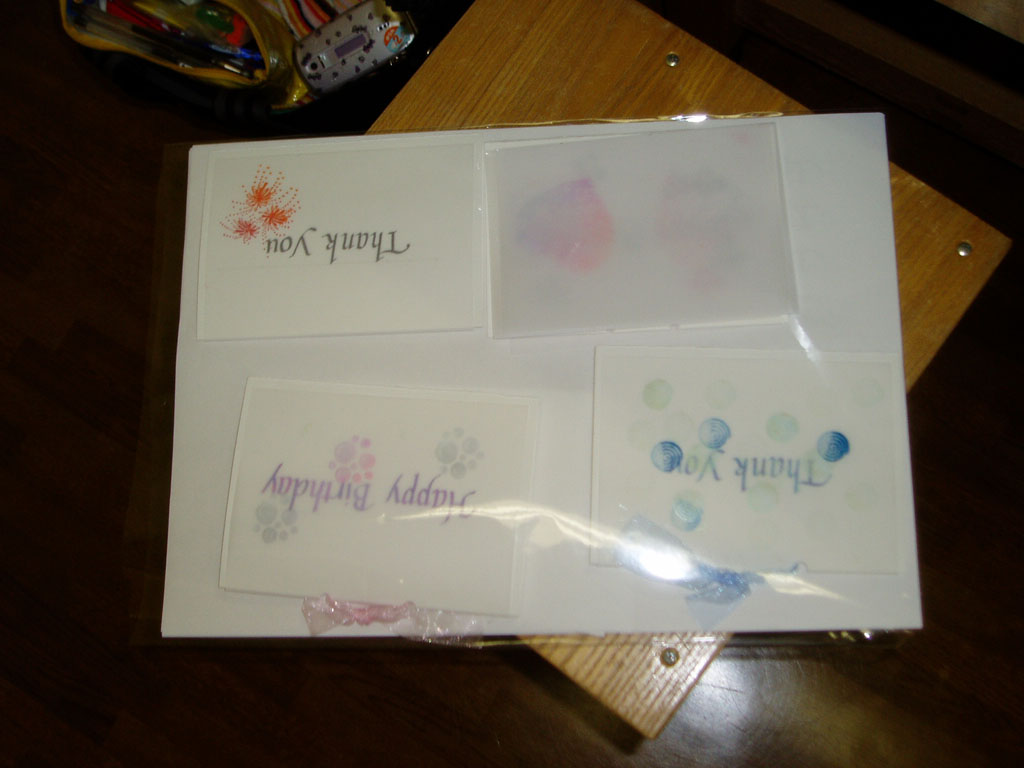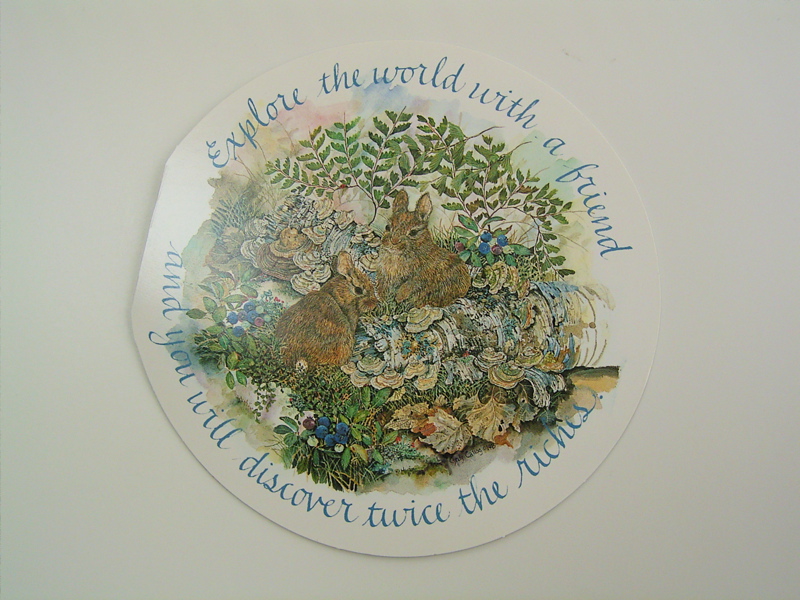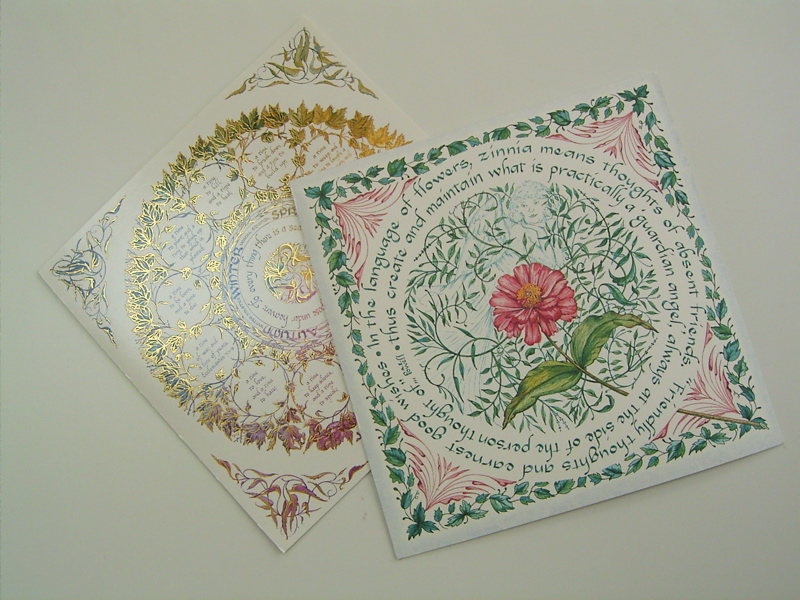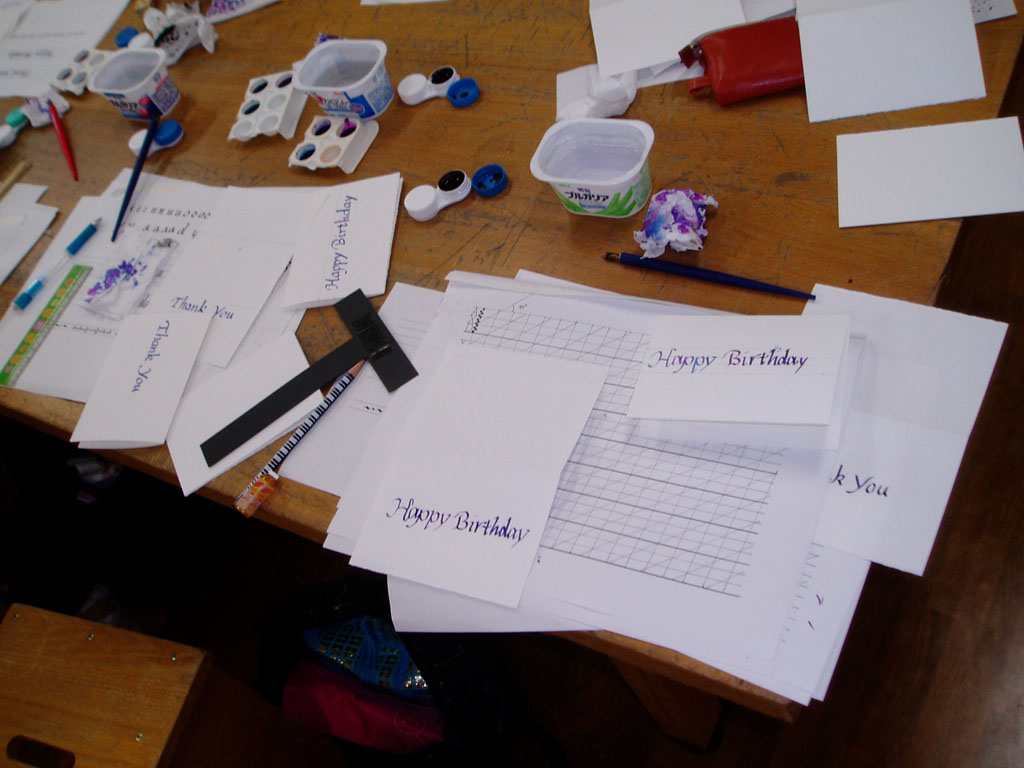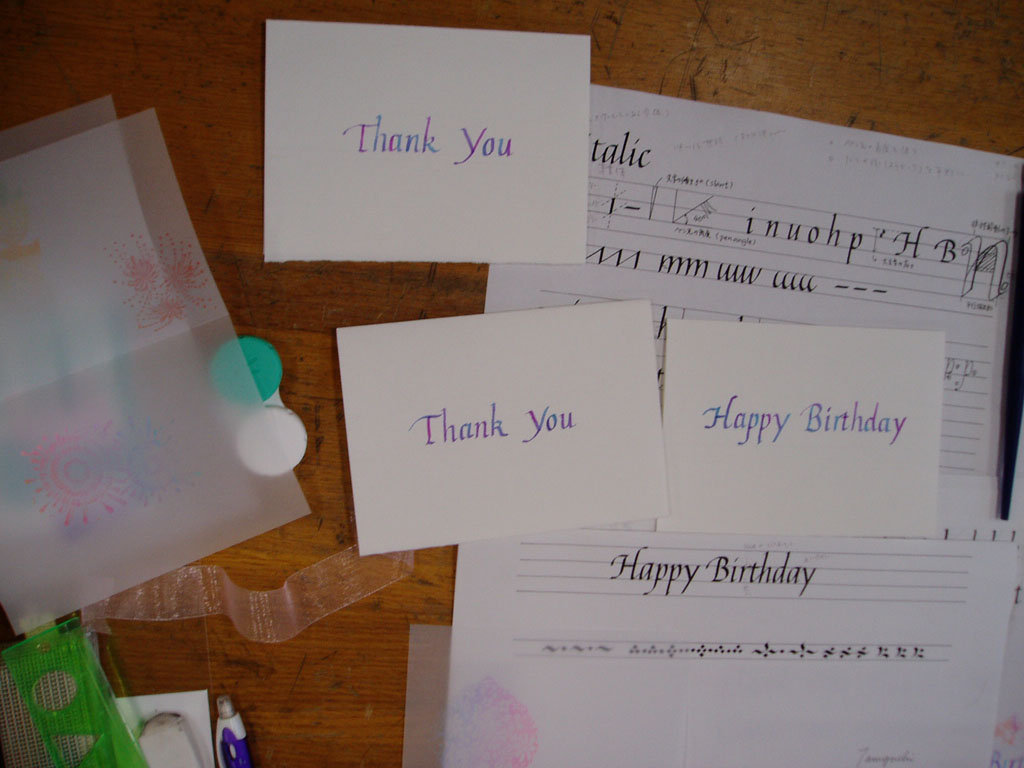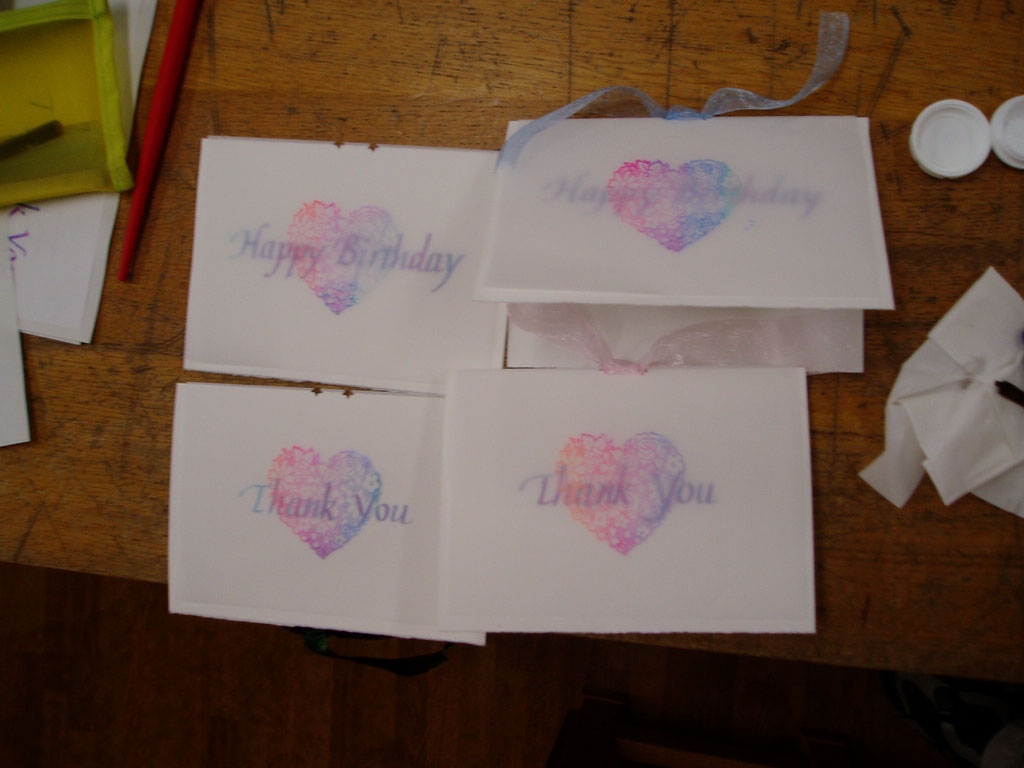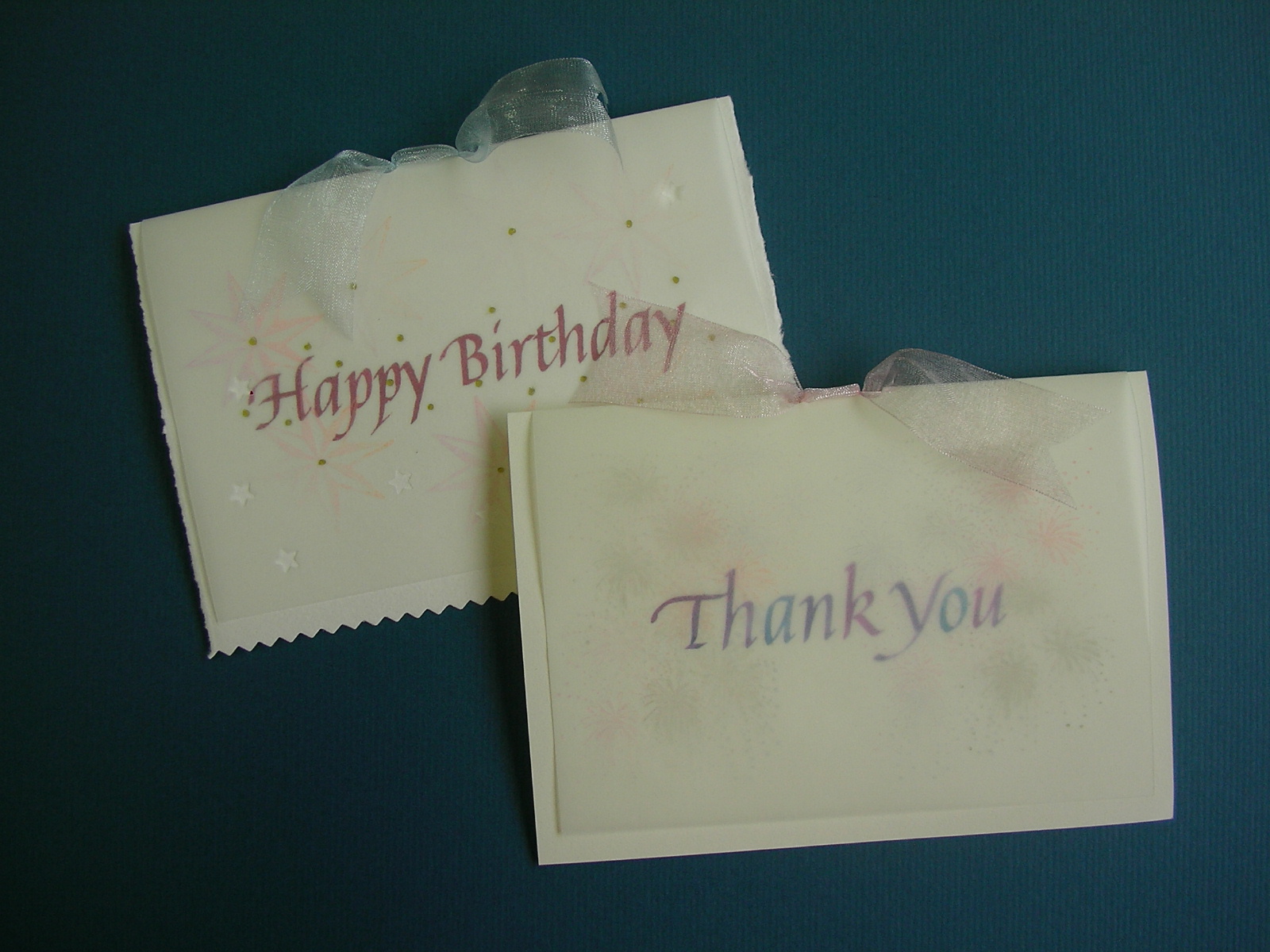
著作権
何日か前の日経新聞に「著作権の保護延長をめぐり議論」の記事が載っていました。
現在日本では文学、美術、音楽の著作権の保護期間は作者の死後50年となっています。今、それを欧米並みに70年に延ばそうといろいろな団体が動いているそうです。
カリグラフィー作品として文章を利用する場合も、著作権のある場合は許可を取らなくてはなりません。個人的に書くには問題はありませんが、公共の場で発表する、はがきやカタログに印刷して販売するとなると、必ず必要です。ですから、著作権の保護期間の過ぎた大昔の人(シェークスピアや聖書)が無難となりますが、この人のこの文章をなんとしても書きたい!となるとこのコピーライトという問題をクリアしなければなりません。
今は50年の保護期間が70年となると、利用したい人にとってみると困りますね・・・・
国によっても違いがあるので、益々気をつけて使用しないとならなくなります。
以前、Nancy Woodの「Dancing Moons」という本からThe voice that beautifies the landという文章を書きたかったので、調べた事がありました。(日本語訳本 ナンシーウッドの「今日という日は贈り物」より「地を美しくする声」)
今日という日は贈りもの―心が生まれ変わる12のアプローチナンシーウッドさんは1936年生まれでアメリカニューメキシコ在住の詩人、作家で、もちろんまだ元気に作家活動をされている方です。(来日した事もあるそうですよ)
さて、これを作品展に出すために制作するにはどうしたら良いだろう・・と考えました。まだ生きているのだから、そうだ、直接許可をもらうのが一番手っ取り早い!!と考え、思い切って手紙を書きました。実はその時には作品はもうほとんど出来上がっていたので、許可してほしいという手紙と共に写真も送りました。住所はわかりませんでしたので、転送してもらう様、出版社にお願いしました。
すぐに返事が来ました!快くOKで、ちゃんと一筆書いてくれたのです。
「いつ、どこに、どんな形で発表しても構わない。但し、売れた場合はその代金の半分を頂きます」
こういう形で自分の文章が使われるのはとても嬉しいとも書いてくださったので、本当に嬉しかったです。これがその時の作品です。という本にも載せてもらえました。
これもちゃんとコピーライトを取っておいたおかげですね。
ルーリングペン・ワークショップ
さて、昨日に引き続きルーリングペンの話題です。
昨日はルーリングペンを使ったワークショップでした。講師はアルゼンチンから来日したBetina Naab(ベティナ・ナアブ)さんです。
参加者は16名。文京シビックセンターの会議室で楽しい一日を過ごしました。
基本のストロークを繰り返し練習して文字、そして単語にしていきました。シンプルだけど、家に帰っても練習出来るやり方です。文字の練習に良い単語(hamburgerやumbrella)でウ〜ん、何事も練習あるのみ、ひたすら書く。
こういう自由に書けるツールはどうしても自己流になり、文字がおろそかになります。適当に書いてもなんとなく様になっているように見えるからです。でも!違う!
大変だけれどきちんと向き合って文字に取り組んでいる人の文字はやはり全然違います。一目瞭然。
文字は書く事によってのみ上達する、と言いますから、どんなツールであれ、練習練習!
さて、今回のワークショップに出席出来なかった方!福岡スタジオ・ポンテで9月にルーリングペン以外にいくつか開催されます。一緒に来日しているフランス人カリグラファーChristelle Reboullet とBetina との作品展も同時に開催されます。
お宝ペン
昨日の話題の続きです。
このルーリングペンのことですね〜!
宝の持ち腐れ?猫に小判?豚に真珠?
もう、なんとでも言ってくださいな。
まともにルーリングペンを使うことのできない私ですが、このペンはmoitor-sさんのご記憶どおり、ルーリングペンを持っていない私にStan Knightが譲ってくださった物です。お値段は忘れてしまいましたが。
もう10年ほど昔のことになりますが、スタンのご自宅で行われたワークショップに幸運にも参加できたのです。先生はGottfried Pottで、ルーリングペンを中心とした正味5日間のワークショップでした。
このルーリングペンはGottfriedのデザインで彼のお友達の製作、と聞きました。インク止めに工夫があるようです。持った感じはですね、わりと軽いですよ。私以外にもお持ちの方はいらっしゃるでしょうが、確かに少ないはずです。Walnut Inkをたくさん使ったのもそのときが初めてでした。ゴットフリードがお茶碗(ご飯茶碗みたいな)にドボドボ大量に溶いて、ペンをつけて使っているのに目をみはりました。
スタンと肩を並べてというのは、もちろん見た目だけの話ですが、英語に???ヘロヘロヘロ・・・となっている私の隣に座ってくださったのは事実です。スタンは憧れの先生なので、最初はとってもとっても緊張して座っていました。でも、カンファレンスに行くと有名な先生も受講者として参加していたりするので、海外ではこういうの普通なんですね。
日本人がひとりだけでしたが、ご飯をみんなで作ったり、散歩や日帰り旅行に行ったりという息抜きもあって、楽しく過ごせました。ただし、みんな朝から晩まですごく練習していました。バッチリと刺激を受けて、いい思い出になっています。でもワークショップは思い出だけじゃだめ、なんですよねえ、自分のその後にちゃんと活かさないと!
ほれ、ルーリングペンも練習練習っと。さて、ゴシック体と言えばWard Dunham!これはカンファレンスで彼のクラスをとったときに、空き時間に削ってくれた竹のペンです。
とってもしなやかで書き味がよくて、大のお気に入りだったのですが、なんと・・・悲しい運命が。
あるとき、カリグラフィー初心者の方向けの講座のときにこのペンも展示していたのです。いつの間にか参加者の方のお子さんに力づよーく使われて、ペキッと先端が折れてしまいました。
人生の中でかなり悲しかった瞬間でした。今じゃあ、観賞するのみ・・・
みなさん、道具自慢するときは気をつけましょう。
ゴッちゃんタイプのルーリングペン
みなさま!あの、しばらく手に入らなかったルーリングペンがほ〜れ、こんなにたくさん!
そうです。ドイツのカリグラファー、Gottfried Pott氏(ゴットフリード・ポット)が愛用のルーリングペン、俗にいう「ごっちゃんタイプのルーリングペン」が、また手に入る様になったようですよ。
実は明日、アルゼンチンから来日しているBetina Naabのワークショップが開催されるのですが、そのクラスで参加者が使うためにアメリカの通販JohnNealに注文したのです。在庫がなかったのですが、なんとか製造元からかき集めてもらいました。John Neal
私はと言えば、昔シアトルで、この道具が一体なんだか知らないまま購入してみたという、道具から入ったタイプでした。
(ですから、明日のBetinaのワークショップは楽しみです。持ち物リストによるとたくさん書いて練習するらしい)
さて、実は、ごっちゃんのルーリングペンではもっとすごい人が身近にいたのです。
そうmojitor-fさんです。
彼女の持っているルーリングペンは、アメリカのStan Knight(スタン・ナイト氏)宅で受けたごっちゃんのワークショップの時に、しかもスタンから分けてもらった、本当のごっちゃんが持っているのと同じタイプのルーリングペンなのですよー!
mojitor-fさん、たしかそうでしたよね?
この頭のところの形が少し違っています。そのタイプを持っている人は、非常に少ないし、ごっちゃんと同じだから、みんな羨望のまなざし・・!しかもスタンと肩を並べて同じ生徒として学んだとなると、すごいですよね〜。
mojitor-fさん、是非こんどブログで紹介してくださいまし!お願いします。
それにしても、今はまだ手元にあるこんなにたくさんのルーリングペン。
見てるだけでただ嬉しい・・・・・フフフ!
2006年08月27日
虫愛づる人々
mojitor-hさんは蜘蛛好きのようですが、クモってだいたいいつも同じところにいますね。
快適な場所なのでしょうね。餌の虫がよくとれるということなのでしょうか。
私も蜘蛛はきらいではありません。見ているだけなら結構楽しいです。
が、飛んでくる虫は苦手でして・・・
子どものときはダンゴムシ飼ったり、テントウムシを箱いっぱい集めたり、セミの抜け殻で遊んだりしてましたが、一体いつから虫に無関心、いや、虫嫌いになってしまったのでしょうか。この夏、田舎で夜カブトムシとりにいくぞ〜と誘われましたが、遠慮しておきました。聞けば、懐中電灯のあかりにものすごい数の蛾が群がってくるそうで、「もし来てたら発狂するかもね」と私のことを話していたらしく・・・留守番しといてよかった。
そのときの狩りの結果、カブトムシとクワガタは現在も元気です。二世も誕生している模様です。
先日クワガタはそろって脱走していましたが、無事発見。最後に見つかった一匹は洗濯機の下から出てきてヨロヨロしてました。(「ゴ」のつく虫と勘違いしてあやうく腕を振り上げるところでした・・・)
さて、見るだけなら大丈夫ということで、写真などを見るのは大好きです。
そこでこの夏感動した本をご紹介!「普通の昆虫図鑑とは違うんだよ〜とってもオススメ」と絵本の読み聞かせ活動をしている人から教えられて購入しました。
昆虫記
ほんとうに、おもしろい写真ばかりです。生きてる!って感じがゾクゾク伝わってきますよ。買ったときはちょっと高いと思いましたが、とっても充実していて見飽きません。
12ヶ月に分けられていて、その月に見られる虫が載っているのも新鮮。カマキリが他の昆虫を捕らえるところとか迫力です。いろいろな虫の羽化も分刻みでたくさん写真があるのがいいな。「糸を使う芸術家」古着屋」「虫の住所」・・・それぞれのページにつけられているタイトルもすてきなのです。
2006年08月26日
alphabet sentences
文字を練習する時、ひとつの文字のみを練習するのではなく、必ず単語、文章で練習しなければなりません。なぜなら、文字はひとつで書かれる事はほとんどなく、必ずつなげて書くからです。そう、スペーシングの練習をしなければならないからです。
そこで一つの文章でaからzまでを書けるアルファベットセンテンス(pangram)で練習します。The quick brown fox jumps over the lazy dog.は最も有名ですよね。
会場が図工室ということで、机が低く書きにくかったのではないかと思います。初めての方には、少々認識難しいかもしれない細めのペン先を使用したので、ペンアングルに戸惑ったり、インクのコントロールがなかなかうまくいかなかったりでたいへんな面もありましたが、カラーインク、スタンプを使用する段には、皆さん、すっかり夢中のように見受けられました。終わる際には、またやってみたい、クリスマスカードはやらないんですかなど、楽しかったという言葉ともにとても興味を持っていただけたコメントをいただき、mojitor-fさんと早起きして遠征してきた甲斐があったというものでした。
このようにまったく初めての方に教えるワークショップは、受講者の反応にあらためて学んだり、確証を得たりといつも初心に戻れる感覚が喜びです。また、うまく進行できるだろうか、ポイントを簡潔に伝えられるだろうか、受講者全員平均的にフォローできるだろうかと心配と緊張でいっぱいで、人数の多い場合は、余計不安ですが、その解決にはアシスタントの力大です。今回もそれは絶大でした。普段ひとり対少人数のせいもあると思いますが、なんかとってもよかったなあ〜〜〜。
カリグラフィー、短い言葉でも手書きで書く楽しさを知りたい人が、まだどこかで待っているかもしれませ〜ん!!!!!